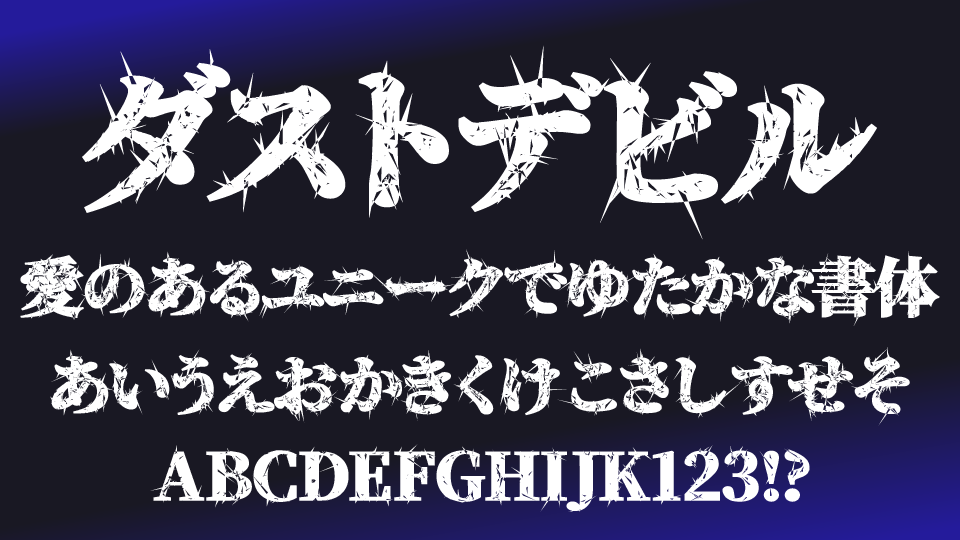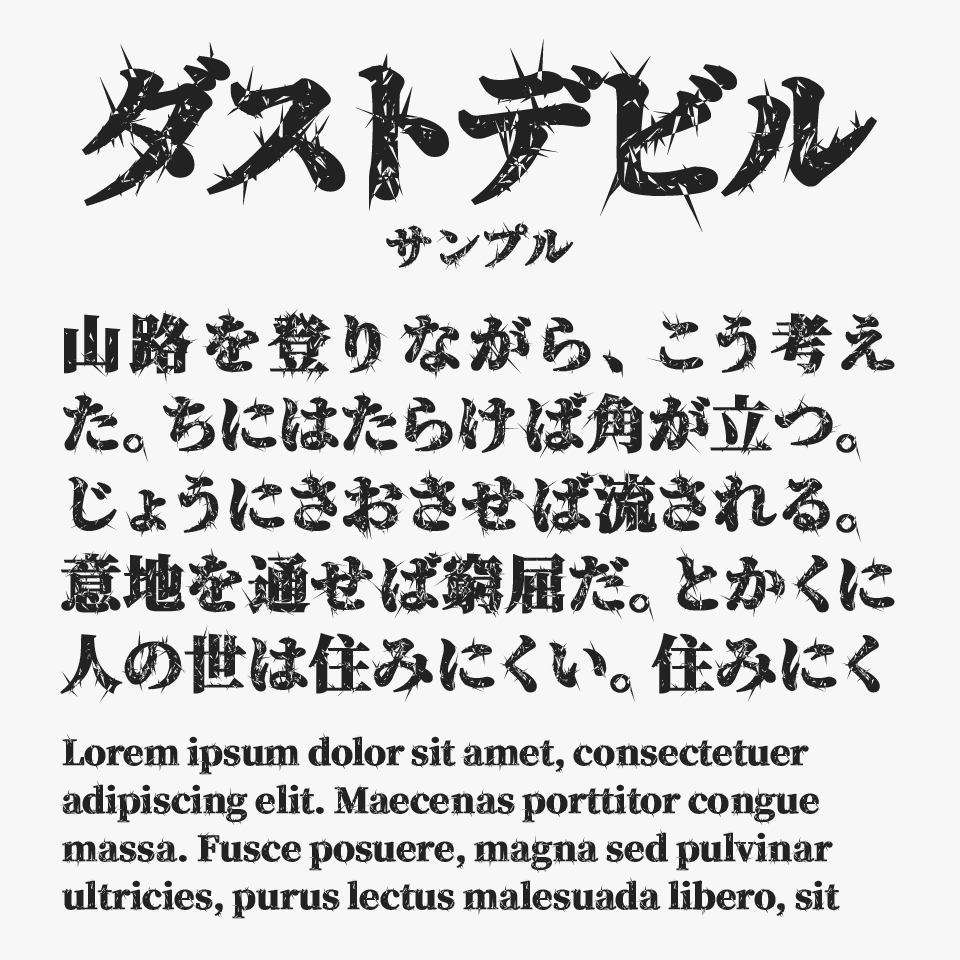
ダストデビルM
ダストデビルMフォントは、源ノ明朝をベースとして、文字全体に鋭い傷や裂け目のような加工が施された、荒々しい質感がかっこいいデザイン明朝体フォントです。
悪魔の角や針のような、砂嵐や爆発、衝撃を受けたようなダメージ表現が印象的で、静かな明朝体とは異なる緊張感が感じられるフォントです。太めの骨格をベースにしているため視認性も高く、力強いタイトルにもよく映えます。
アクションゲーム、ホラー、バトル作品、映画ポスター、ロックイベント、サムネイルなど、激しさや危険な雰囲気を表現したい場面にぴったりです。グランジ加工を加えたデザインとも相性が良く、迫力あるビジュアルが作れます。